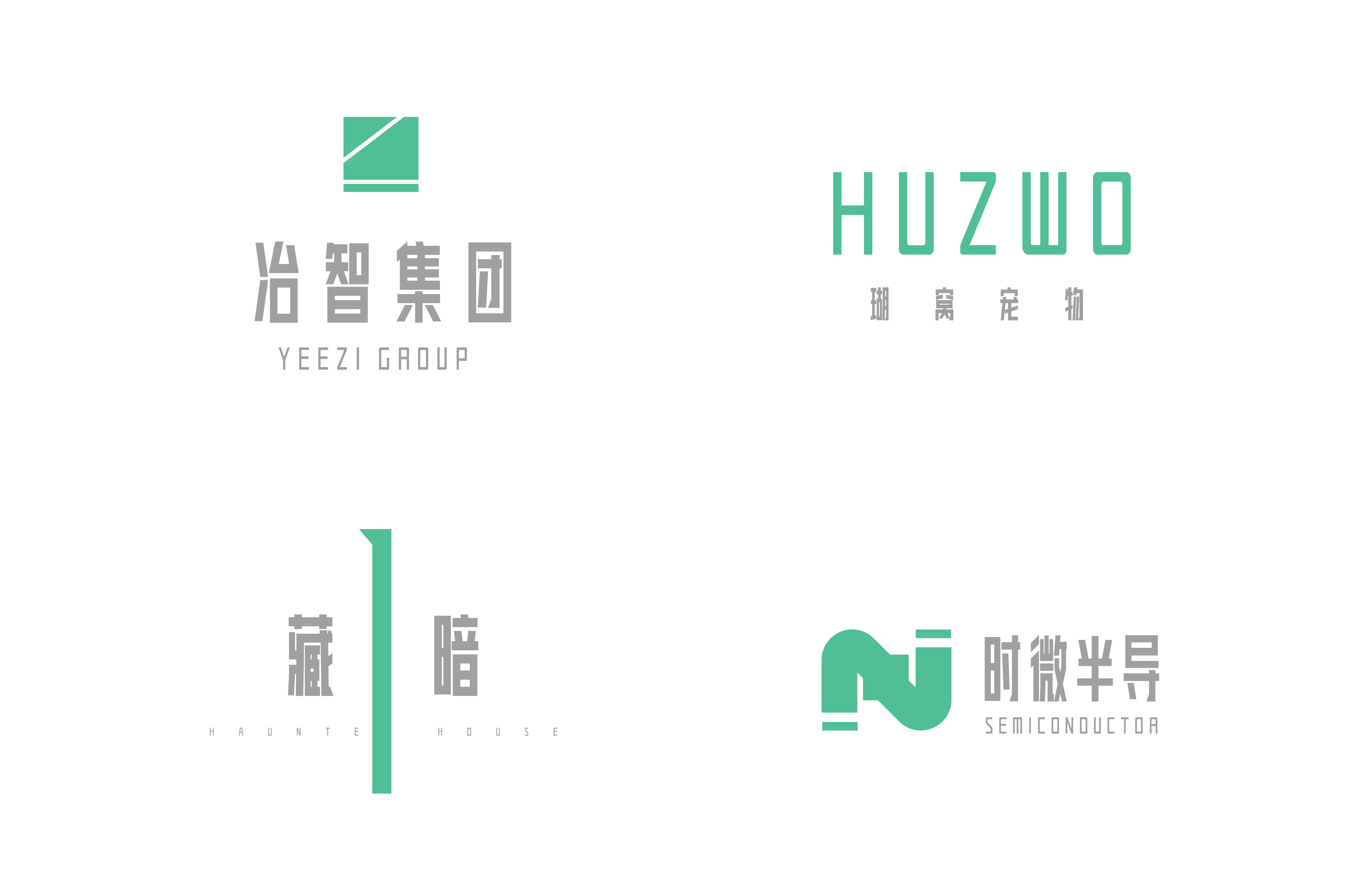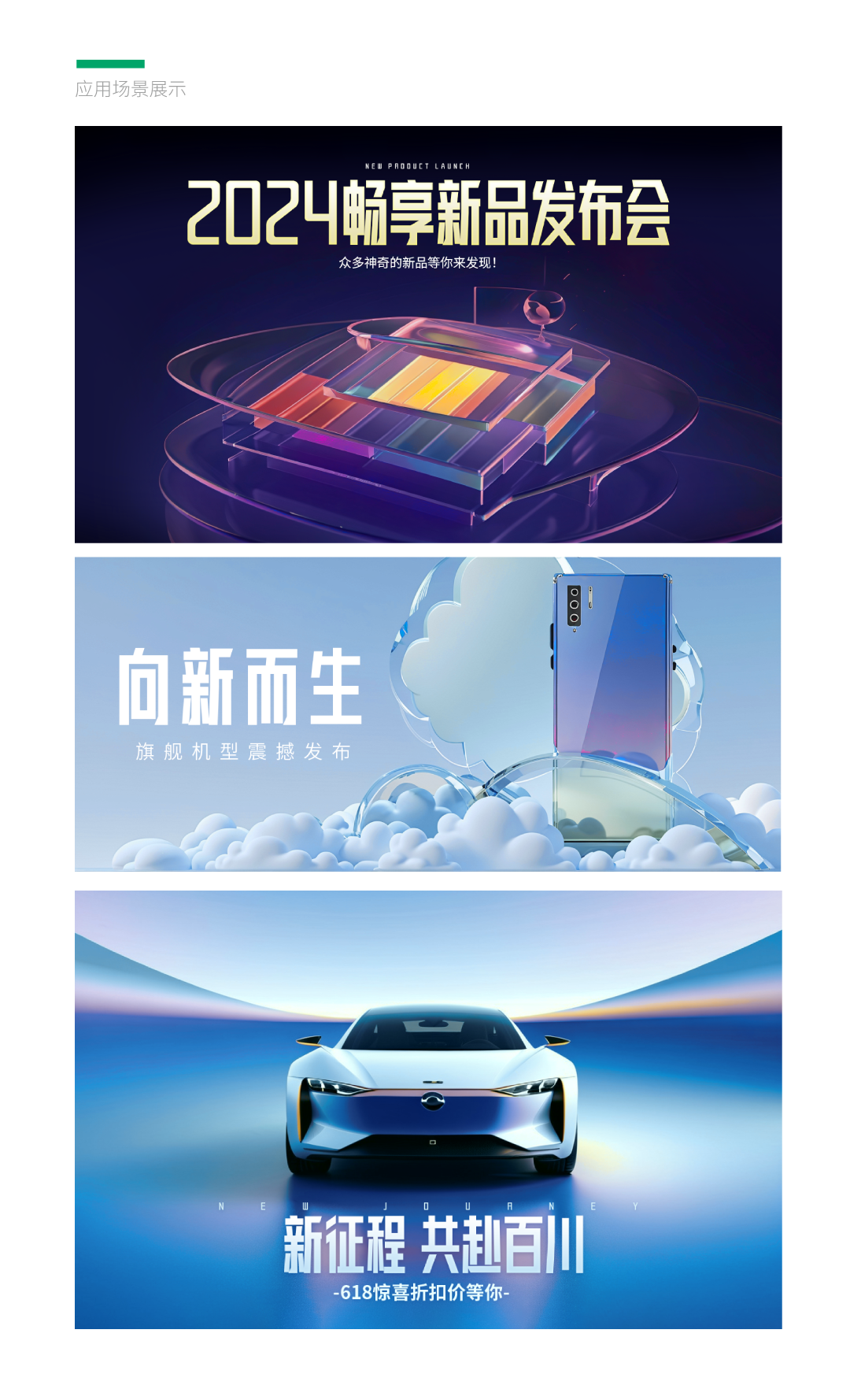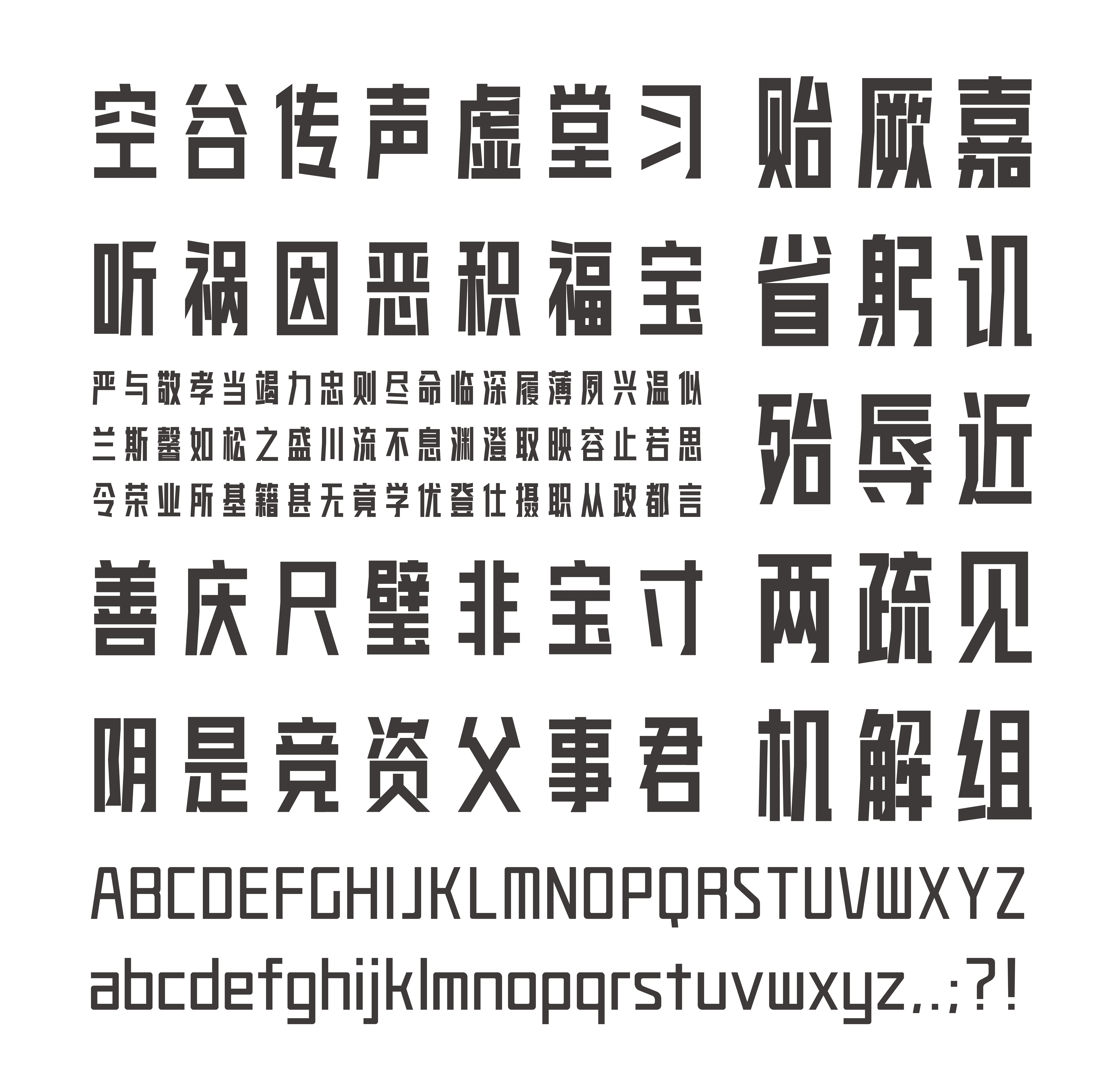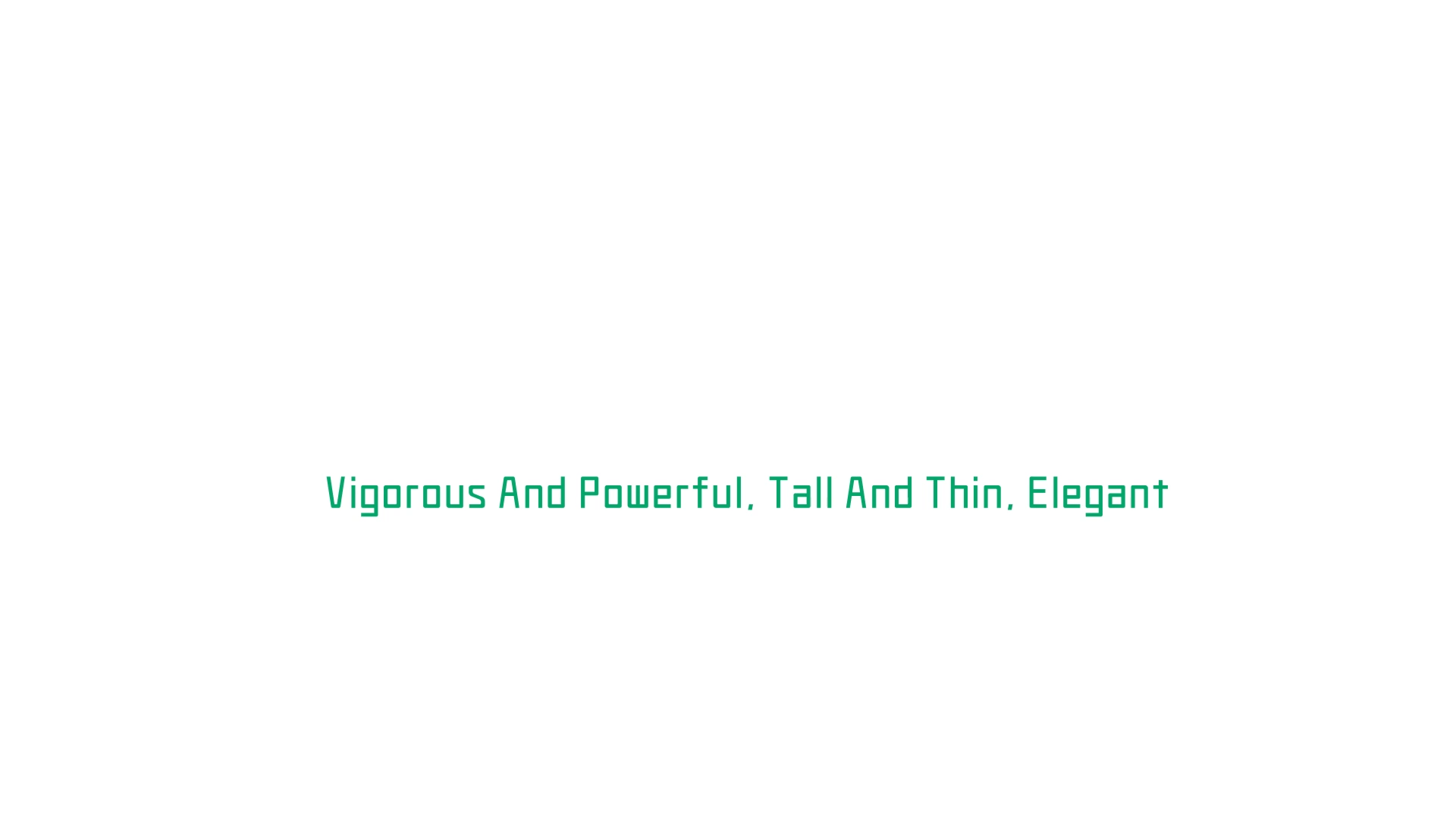
方正苍颜黑
方正苍颜黑,这款字体结构工整、笔画清晰,兼顾美观与易读性,适用于标题、正文、海报、包装、LOGO 等多种场景。字形优雅稳定,风格百搭耐看,适配日常排版与创意设计,让文字呈现更舒适、更具质感。方正苍颜黑一笔一画,皆是细节,以均衡的比例、流畅的线条打造舒适视觉体验,字形端正大气,风格简约现代。无论是商业设计、品牌宣传还是日常排版,都能轻松驾驭,让文字更有格调与力量。方正苍颜黑字体下载。
《方正苍颜黑》是一款瘦长的黑体字,主要笔画特征硬朗、中宫偏大、字体呈瘦高形状、笔画细节简洁耐看具有冲击力,字体整体感受苍劲有力,瘦高的字形体现出优雅的感觉,很有“颜”。本款字适用于品牌、招牌、广告、包装、游戏、设计等众多场景。